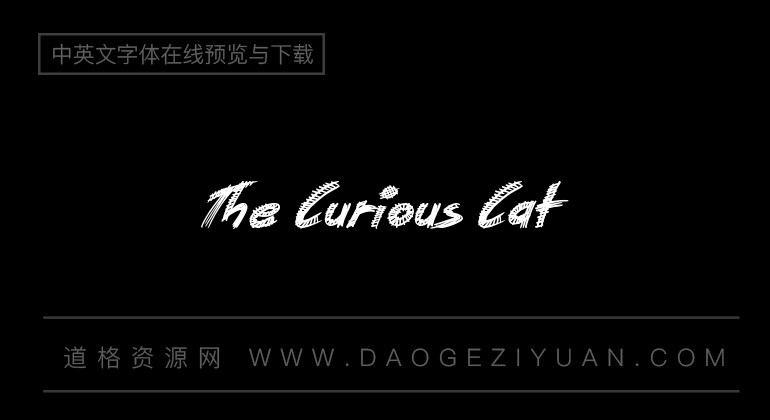
The Curious Cat 是一种手写风格的英文字体,由设计师朱利安·史密斯(Julien Smit)于2019年创建。该字体采用了一种独特的方式,将大小写字母的连笔和线条互相交织,形成了一种具有艺术感和个性化的字体风格。 The Curious Cat 字体主要用于印刷和数字设计中的标志、标题和宣传材料等方面。它包含了大写字母、小写字母、数字和标点符号,共有近300个字符。该字体的风格适合用于表达创新、艺术、个性和活力等特点的内容。 此外,The Curious Cat 字体还提供了多种字重和变体,以满足不同设计需求的使用。内容介绍
The Curious Cat是一款非常不错的手写艺术字体,具有很好的视觉感,适合于文化类的宣传设计、商业类品牌的广告和产品包装设计以及个性化文字排版等较多场景。